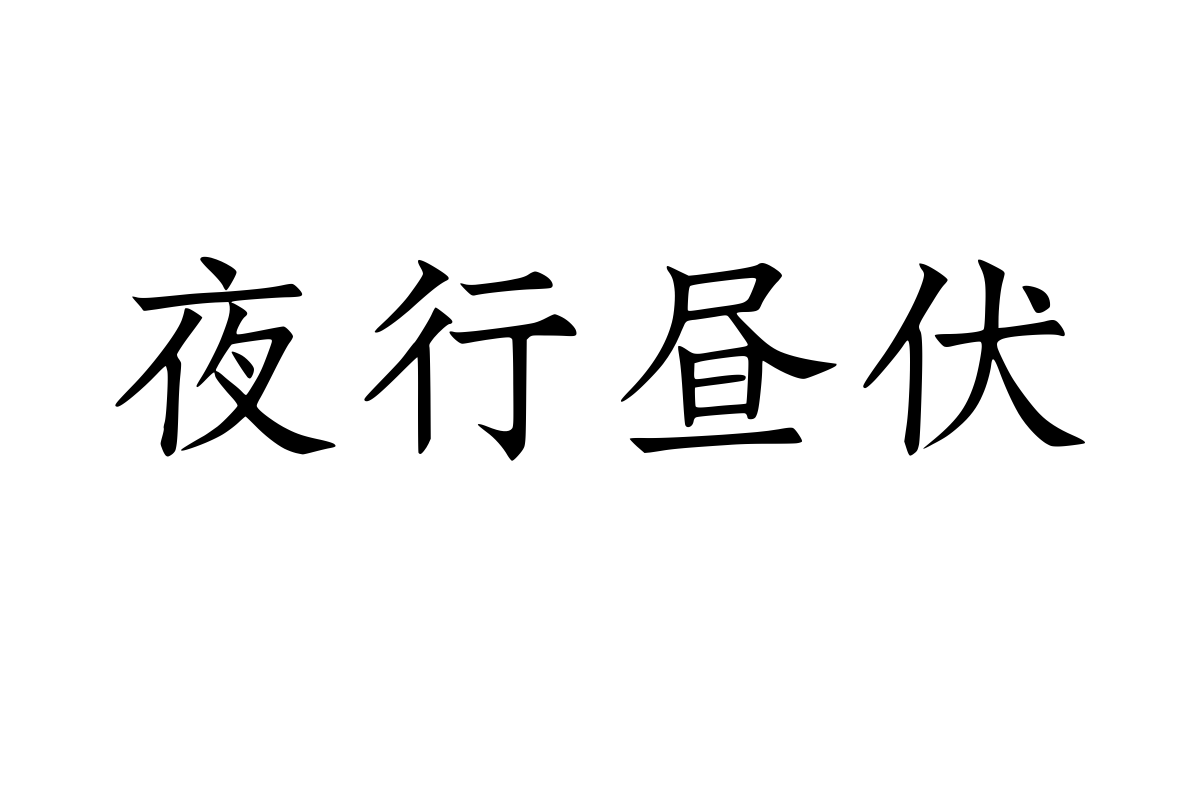
汉呈王天喜雅楷字体是一款具有独特韵味的中文书法字体,它以简洁、流畅的线条为特点,展现出一种优雅而古朴的美感。这款字体适用于各种需要展现传统文化氛围的场合,如书籍、杂志、广告等。
汉呈王天喜雅楷字体的特点如下:
1. 线条流畅:汉呈王天喜雅楷字体的笔画线条流畅自然,没有过多的装饰性细节,给人一种简洁明快的感觉。
2. 结构严谨:该字体的结构严谨,每个字的比例和位置都经过精心设计,使得整体看起来既和谐又统一。
3. 风格独特:汉呈王天喜雅楷字体的独特之处在于它的线条处理和结构布局,使得字体既有古典韵味,又不失现代感。
4. 适用范围广泛:由于其独特的风格和特点,汉呈王天喜雅楷字体适用于多种场景,无论是正式的商务场合还是文艺的文艺作品,都能完美融入。
总的来说,汉呈王天喜雅楷字体是一款具有很高艺术价值和文化内涵的字体,适合用于各种需要展现传统文化气息的场合。